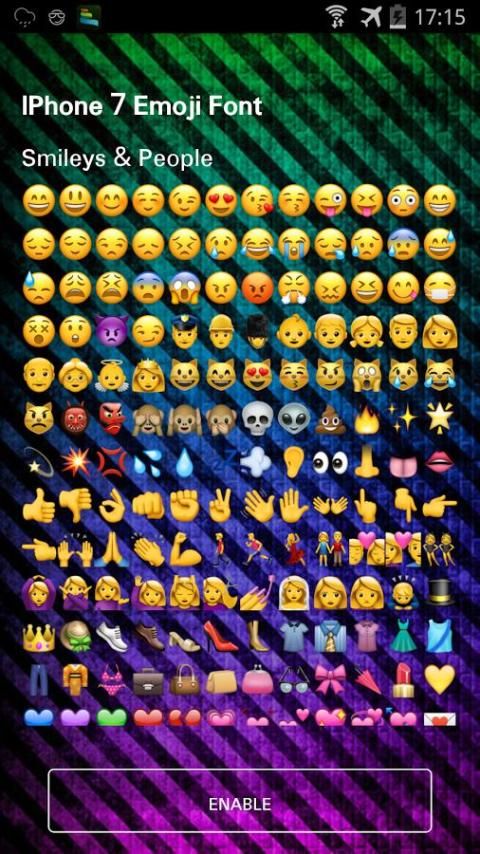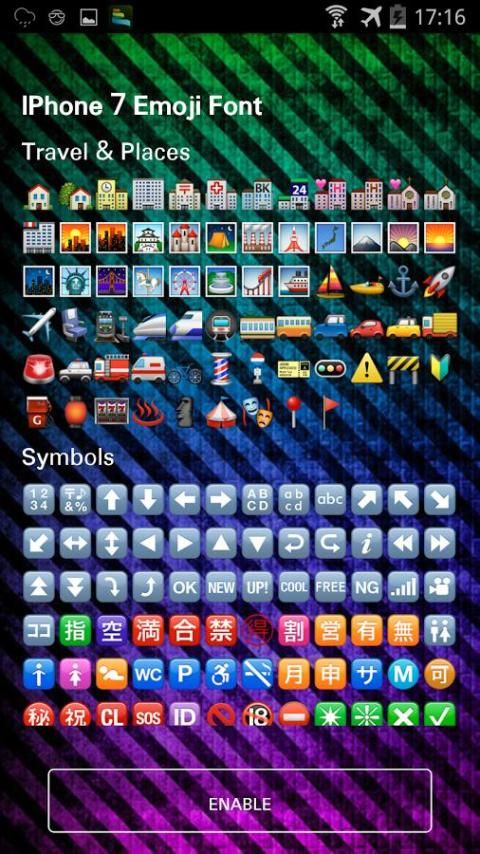
iPhone Emoji Font adalah plugin yang dirancang khusus untuk pengguna Emoji Font Changer, termasuk puluhan ikon emoji dan wallpaper emoji, yang dapat mempersonalisasi perangkat dengan mudah.
iPhone Emoji Font adalah huruf iPhone 7 Emoji, datang dari iOS terbaru 10.
Apa yang dapat Anda nikmati di iPhone Emoji Font:
- Nikmati emoji huruf iPhone untuk Android, Gunakan App ini.
- Ubah emoji sistem anda, dan itu akan menunjukkan kepada Anda apa pengguna akan lihat.
- iPhone Emoji Font mengkustomisasi font yang emoji ponsel Anda untuk font yang iPhone emoji ini.
-Anda tidak perlu Keyboard Emoji untuk menikmati emoji ini.
- GUNAKAN font iphone emoji, Anda dapat melihat emoji iphone di SEMUA IM (Seperti Snapchat, Gmail dan sebagainya)
- Font emoji 3 iphone emoji adalah nama aplikasi.
iphone emoji font untuk flipfont 3 mudah untuk mengubah font sistem! font yang indah, suasana yang indah!
emoji huruf 3 iphone emoji sangat lucu.
Silakan menikmati ini iPhone Emoji untuk Android flipfonts untuk menyediakan Anda dengan kemampuan untuk mengubah perangkat Anda emoji.
iPhone emoji huruf 3 datang dari iPhone 7.
emoji iPhone adalah yang terbaik dari sistem font emoji lainnya.
Ambil iPhone Emoji Font 3, Anda dapat secepatnya menggunakan emoji iPhone Baik dalam sistem android.
iPhone emoji font untuk android yang satu ini. Nama ini iPhone Emoji font yang 3. ikon iPhone dapat menemukan di dalamnya. Anda memilikinya, Anda juga memiliki keyboard iPhone. iPhone emoji atau huruf emoji Samsung, Anda dapat beralih pada aplikasi.